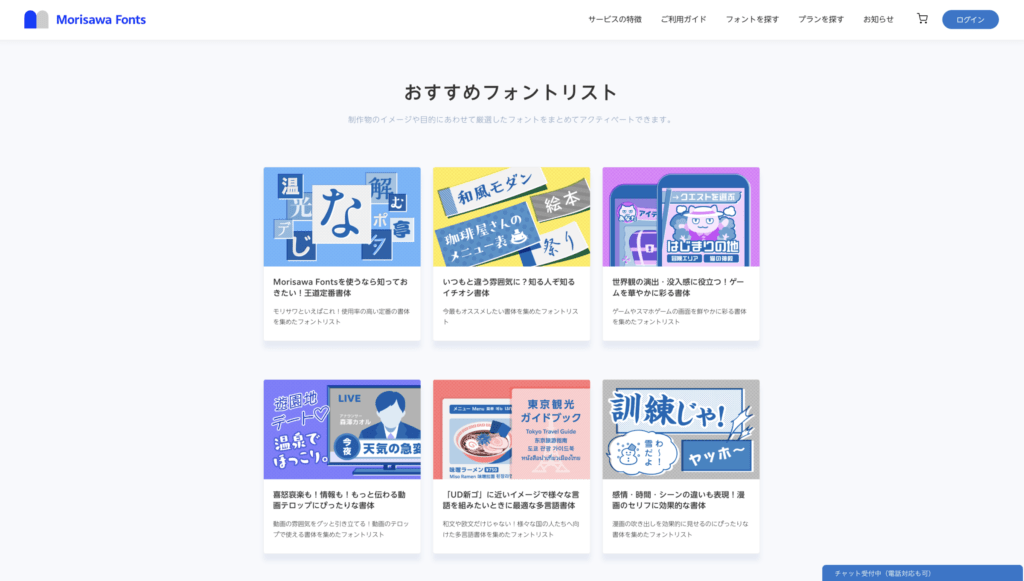
モリサワ Fontsにて定番書体や動画テロップ向けなど新たな「おすすめフォントリスト」を公開、フォント検索機能も拡張
株式会社モリサワは、フォントサブスクリプションサービス「Morisawa Fonts」で、定番書体20ファミリーや動画テロップに最適な14ファミリーなど、制作物のイメージや目的にあわせて厳選した「おすすめフォントリスト」を新たに公開しました。また、その他様々な新機能を追加した。
「おすすめフォントリスト」は、2,000書体以上のフォントライブラリーの中から、より最適な書体を選びたいユーザーに向けて、厳選したおすすめ書体を種類別にまとめたもの。リストのフォントは、まとめてアクティベートすることやコレクション登録が可能なため、効率的にフォントを管理・利用できる。
【新しいおすすめフォントリスト】
1.Morisawa Fontsを使うなら知っておきたい! 王道定番書体
モリサワの書体の中でも特に知名度や人気の高い、定番とも言える書体を集めたリスト。初めてモリサワの書体を使用されるユーザー、定番書体を押さえておきたいユーザーに向けて作られている。
2.いつもと違う雰囲気に? 知る人ぞ知るイチオシ書体
定番とは一味違う雰囲気を持つ書体のリスト。使い慣れた書体があるユーザーにとっても、新たな発見がある。
3.世界観の演出・没入感に役立つ! ゲームを華やかに彩る書体
主にゲームのUIなどに最適なリスト。特徴の異なる様々なデザインを持つ書体を揃え、SFやファンタジー、さらには癒し系まで、幅広いジャンルに合った雰囲気を演出することができる。
4.喜怒哀楽も! 情報も! もっと伝わる動画テロップにぴったりな書体
動画のテロップや字幕での使用に最適な書体のリスト。喜怒哀楽などの感情の表現や、可読性を重視して正確に情報を伝えたいときなど、動画の雰囲気を引き立てられる特徴的なデザインを持った書体を揃えている。
5.「UD新ゴ」に近いイメージで様々な言語を組みたいときに最適な多言語書体
150を超える言語を共通の印象で併記することができる、UD新ゴとClarimo UDのシリーズで構成されたリスト。WebサイトやSNS、看板やレストランのメニューなど、多様な国・地域に向けた情報発信の場で役立つ。
6.感情・時間・シーンの違いも表現! 漫画のセリフに効果的な書体
漫画の吹き出しやタイトルなどでも使えるデザインの書体を集めたリスト。インパクトのあるデザイン書体やアンチック体のほか、読みやすさを考慮した明朝体やゴシック体もピックアップしている。